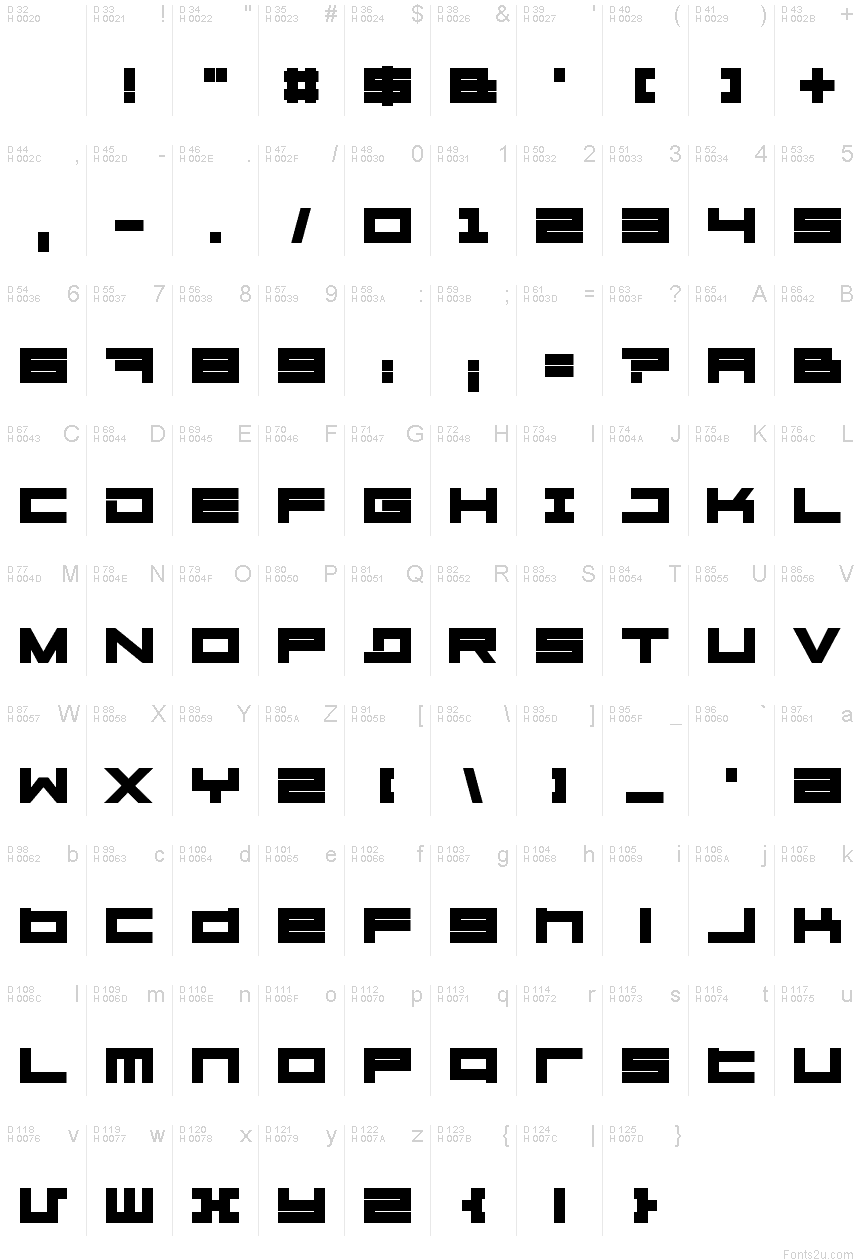
Megaton Heavy
<p>Megaton Heavy od dustBUST Fonts to darmowy krój pisma typu techno display, wyróżniający się wysokimi, prostokątnymi formami, długimi poziomymi belkami i sporymi czarnymi odstępami, które sprawiają, że litery wyglądają na zaprojektowane technicznie, a nie przytłaczająco. Rytm pisma wynika z powtarzających się prostych cięć i oddzielonych kresek, co nadaje projektowi twardy, elektroniczny charakter, przypominający bardziej oznaczenia na panelach sterowania niż neutralny font bezszeryfowy.</p>
<p>Dzięki takiej strukturze Megaton Heavy jest naturalnym wyborem do tytułów gier, plakatów sci-fi, ulotek muzycznych, szkiców logo i nagłówków UI. Segmentowane belki i pionowe obramowanie nadają również krótkim tekstom przekonujący klimat centrum sterowania, zwłaszcza na opakowaniach, w brandingu wydarzeń czy grafikach ekranowych, które wymagają wyrazistego, syntetycznego sznytu.</p>